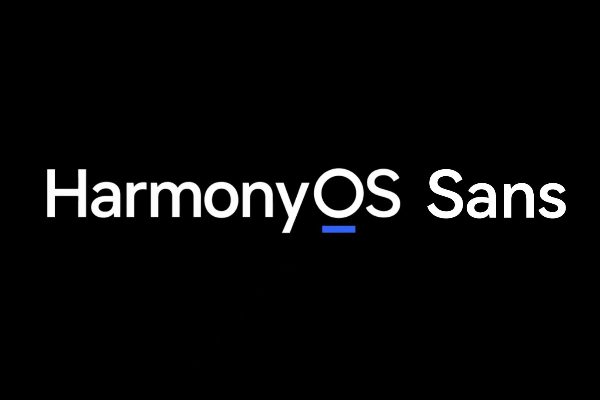
HarmonyOS Sans Condensed Black
HarmonyOS Sans Condensed Black是一款兼具现代科技感与简约美学的黑体字库,以修长字形与利落设计著称。作为HarmonyOS字体家族的重要成员,其设计聚焦全球化视野下的多元应用场景,将功能性与普适性深度融合,成为科技领域与创意设计的理想选择。 字形修长的设计赋予其独特的视觉张力,中宫适中的排布让字符在保持紧凑感的同时,重心居中的平衡结构确保了阅读的稳定性。笔型采用利落直角设计,搭配粗且均匀的笔画线条,方头笔画与断开式连接的细节处理,既强化了字体的力量感,又避免了视觉拥堵,展现出鲜明的几何美学特质。 作为免费商用字体,HarmonyOS Sans Condensed Black凭借多字重特性,可灵活适配从标题到标识的各类排版需求。无论是科技产品界面、品牌视觉系统,还是现代海报设计,其简约而富有冲击力的风格都能精准传递清晰有力的视觉语言,成为连接创意与功能的实用型字库。